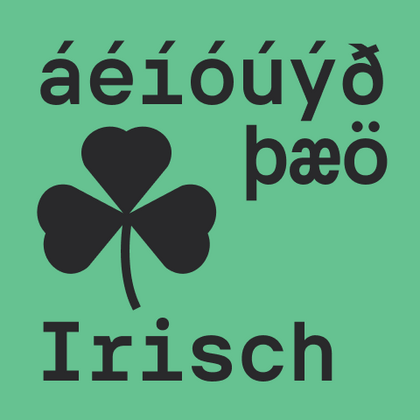
Selección de Irlandés fuentes
La tipografía irlandesa tiene un encanto distintivo que las fuentes en idioma irlandés de TypeType preservan maravillosamente en aplicaciones de diseño. Estas familias tipográficas, con sus símbolos característicos y formas de letras estilizadas, son perfectas para proyectos relacionados con la cultura celta o trabajos creativos contemporáneos. Explora la colección de TypeType y descubre fuentes que darán a tu texto una expresividad única y un carácter auténtico.
Selecciona una fuente adecuada que admita Irlandés idiomas. Una enorme colección de familias de fuentes para cualquier propósito y tarea: escribir grandes conjuntos de texto, diseñar títulos para sitios web y publicaciones impresas, imprimir sobre textiles y otros materiales, diseñar letreros y carteles.
Cada una de las fuentes presentadas contiene el alfabeto Irlandés. Una amplia selección de símbolos, moneda y signos de puntuación, estilos de fuente y funciones OpenType le permitirán utilizar una fuente para diferentes proyectos. Los caracteres latinos extendidos que contienen signos diacríticos ampliarán la usabilidad de la fuente en diferentes países.
Cada fuente es técnicamente impecable. Muchas fuentes de la colección incluyen un estilo variable, que puede usarse para crear un estilo único para tu proyecto.
Puedes utilizar etiquetas para seleccionar el estilo de fuente o carácter que necesita: geométrico o dinámico, universal o clásico, dinámico o suave. También será conveniente buscar por finalidad: fuente para revistas o sitios web, para emails o publicidad.
Cualquier fuente de la colección se puede personalizar técnica o gráficamente. Con la personalización, puedes agregar o eliminar una letra, agregar el logotipo de una empresa o reducir la composición del efectivo para aligerar el peso del archivo de fuente.
TT Quaris is an exquisite, modern high-contrast sans whose design balances between soft and sharp. The glyph shapes in the font are fluid and tend towards roundness, yet there are also sharp elements.
TT Ricordi Allegria is a sleek and intelligent contemporary Florentine grotesque.
TT Bakers is a fluid serif with a gentle and lively character. This font is like freshly baked goods: it’s warm and soft, especially in its bolder weights.
TT Modernoir is a display sans serif with dynamic proportions. Fluid lines and delicate Art Nouveau forms in this typeface blend seamlessly with the rhythmic flow and improvisational freedom of jazz.
TT Moons is a slim and contrast serif. This font family works especially smart in classic design themes. TT Moons is a typeface of the glyptal modern typeface.
TT Ricordi Greto is an experimental project, inspired by a floor plaque dating from 1423 found in the Basilica di Santa Croce, Florence.
TT Firs Neue is a contemporary reincarnation of the good old TT Firs sans serif.
TT Marks ofrece un estilo manuscrito con un ritmo dinámico, un carácter entrañable y un atractivo nostálgico inspirado en el arte clásico de la rotulación a pincel. Este oficio —donde artistas expertos pintaban a mano los letreros de tiendas con pinceles y gran técnica— está viviendo un merecido renacimiento en el mundo del diseño actual.
TT Fellows is a humanist sans serif with a mechanical touch.
TT Disruptors es una tipografía manuscrita dibujada con rotulador, dúctil y expresiva. Su diseño es único: bordes desgastados, trazos de grosor variable y ascendentes y descendentes alargados le otorgan una textura dinámica y artesanal. La personalidad de esta fuente es enérgica y emocional, pero también cálida y con alma.
TT Gentlemens is a dynamic handwritten typeface that combines the seriousness and precision in writing with elegance and sophistication. It has the character and style of a true gentleman: restrained and always appropriate, yet confident and striking.
TT Ramillas is a fully reconsidered high contrast transitional serif, which is perfectly adapted to modern realities and requirements.
TT Gertika is a geometric sans serif with a dynamic character and a dancing rhythm. This font’s idea originates from the lettering featured on an American poster from the late 1930s.
TT Biersal is a display sans serif with a free-spirited, playful, and adventurous nature. The concept of this font was sparked by a German poster from the early 1930s.
TT Paplane is a squared-looking display sans serif.
TT Tricks is a modern text serif with a design reflecting the style of Transitional serifs. This font has a calm, elegant, and moderately stern character.